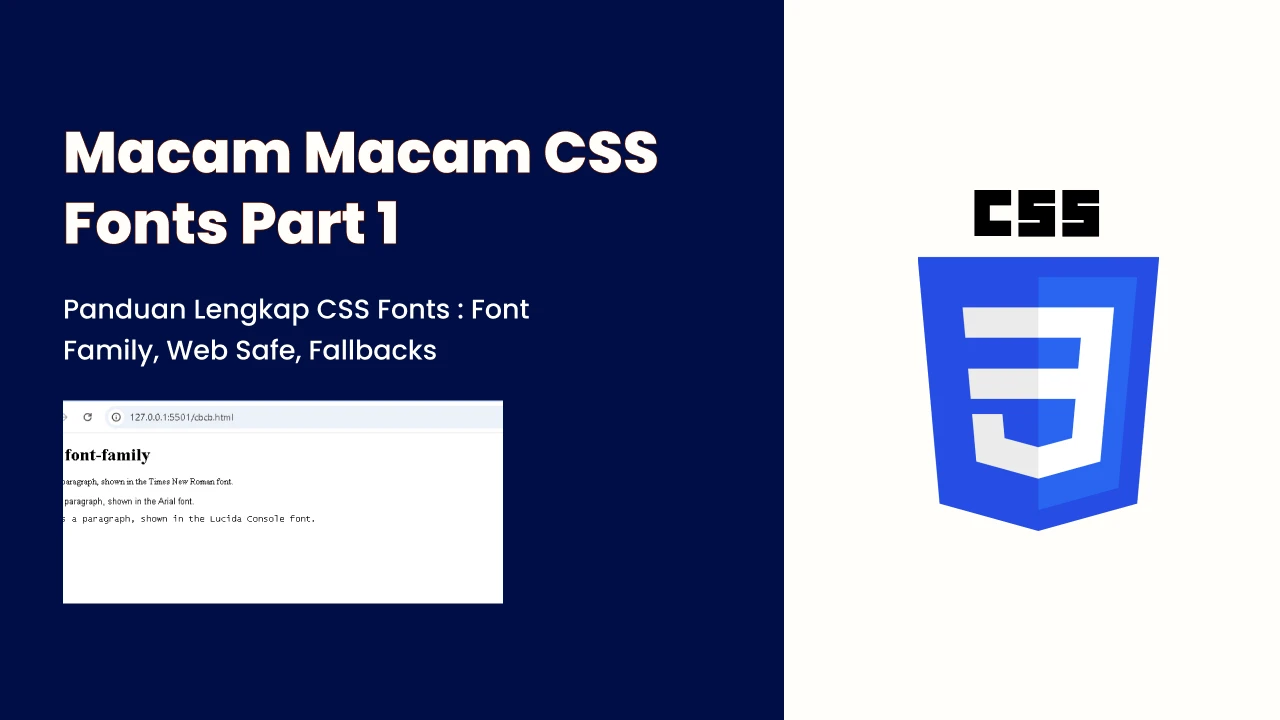
Font dalam CSS
Memilih font yang tepat untuk website sangat penting!
Kenapa Memilih Font Itu Penting?
Font yang digunakan bisa sangat mempengaruhi bagaimana pengunjung merasakan tampilan website.
Font yang tepat bisa membantu membangun identitas merek.
Font yang mudah dibaca membuat teks lebih nyaman dibaca.
Warna dan ukuran font juga berpengaruh terhadap kenyamanan pengguna.
Properti font-family
dalam CSS
Untuk menentukan font di CSS, gunakan font-family
.
Jika nama font terdiri dari lebih dari satu kata, gunakan tanda kutip ("").
Contoh Penggunaan:
berikut hasilnya
Apa Itu Web Safe Fonts?
Web Safe Fonts adalah font yang tersedia di hampir semua perangkat dan browser.
Artinya, saat kita menggunakan font ini, kemungkinan besar tampilannya akan sama di berbagai sistem operasi dan perangkat.
Namun, tidak ada font yang 100% tersedia di semua perangkat. Ada kemungkinan font tertentu tidak terinstal, sehingga tidak bisa ditampilkan dengan benar.
Kenapa Harus Menggunakan Fallback Fonts?
Karena tidak ada font yang 100% tersedia di semua perangkat, kita harus menggunakan fallback fonts (font cadangan).
Caranya:
Saat menulis kode CSS untuk font, kita bisa menyertakan beberapa pilihan font. Jika font pertama tidak tersedia, browser akan mencoba font kedua, lalu ketiga, dan seterusnya. Daftar ini harus diakhiri dengan jenis font generik seperti sans-serif
atau serif
.
Contoh Kode CSS dengan Fallback Fonts:
Penjelasan:
Jika Tahoma tidak tersedia, browser akan mencoba Verdana.
Jika Verdana juga tidak ada, browser akan menggunakan font default dari kategori sans-serif.
berikut hasilnya
Apa Itu Font Fallbacks?
Font fallback adalah cadangan font yang digunakan jika font utama tidak tersedia di perangkat pengguna.
Ketika kita menentukan font dalam CSS, sebaiknya kita memberikan beberapa pilihan font, sehingga jika yang pertama tidak tersedia, browser akan mencoba yang berikutnya.
1. Serif (Elegan & Formal)
Serif memiliki garis kecil (serif) di ujung hurufnya.
Contoh Font & Kodenya:
berikut hasilnya